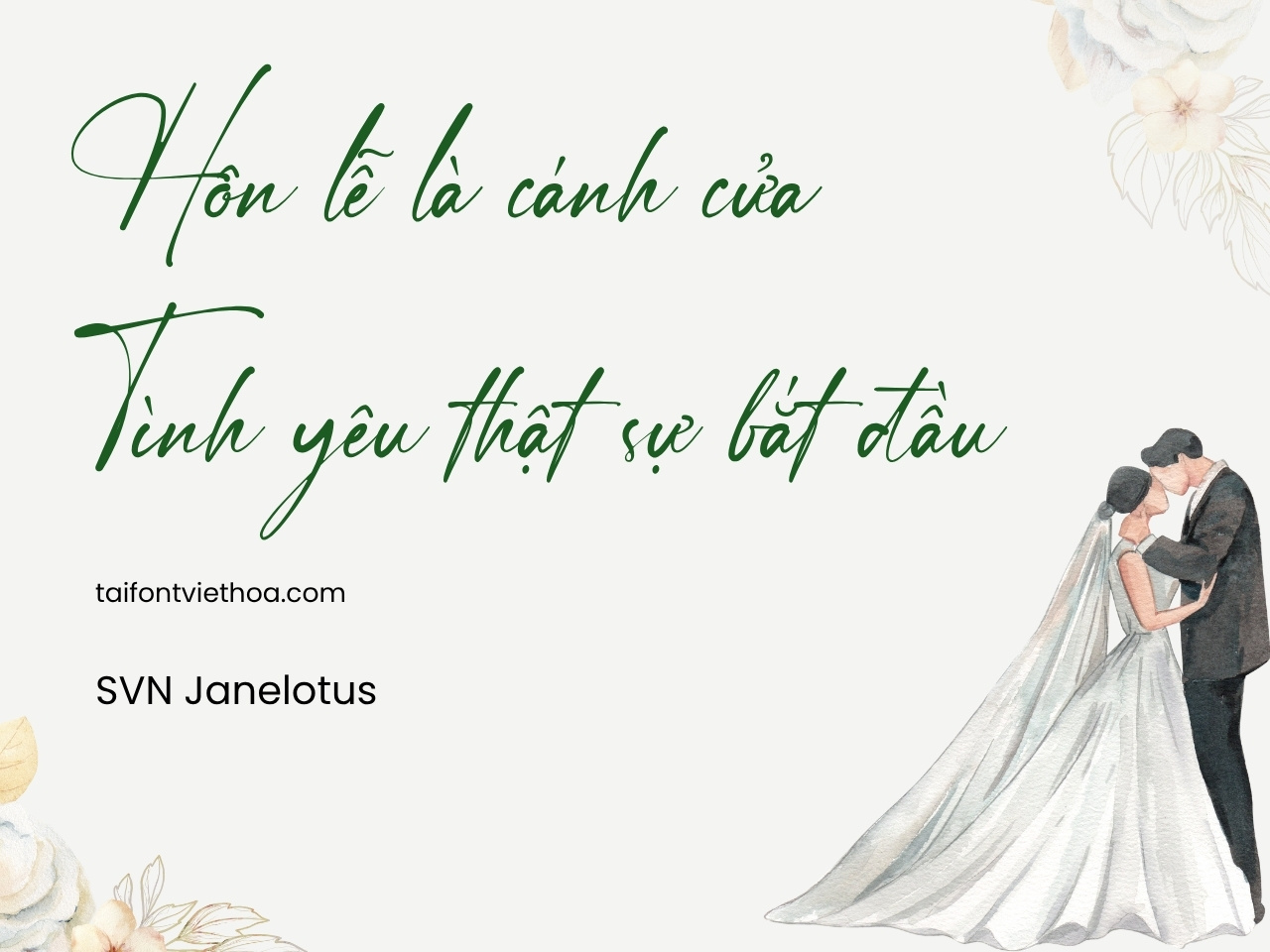
Font việt hóa SVN Janelotus
Giới thiệu về font SVN Janelotus – Kiểu chữ script viết tay mềm mại, tinh tế và duyên dáng
SVN Janelotus là phiên bản Việt hóa của font Janelotus – một kiểu chữ script mang phong cách viết tay uyển chuyển, nhẹ nhàng và đầy cảm xúc. Font được thiết kế để truyền tải sự thanh lịch, bay bổng và nữ tính, rất phù hợp cho các dự án thiệp cưới, lời chúc, thiết kế mỹ thuật và các sản phẩm sáng tạo cá nhân.
Phiên bản Việt hóa của SVN Janelotus đã được Taifontviethoa.comchăm chút kỹ lưỡng, hỗ trợ đầy đủ dấu tiếng Việt cùng hơn 60 ngôn ngữ khác. Font giữ nguyên nét mềm mại, uyển chuyển của bản gốc, giúp các nhà thiết kế dễ dàng áp dụng trong nhiều dự án sáng tạo với phong cách nữ tính và duyên dáng.
Thiết kế viết tay uyển chuyển – Lý tưởng cho thiệp cưới và thương hiệu mỹ phẩm
SVN Janelotus sở hữu các nét chữ mềm mại, mảnh mai, liền mạch với độ nghiêng nhẹ nhàng và các ligature tinh tế tạo nên sự hài hòa và bay bổng trong tổng thể thiết kế. Font mang lại cảm giác duyên dáng, sang trọng và rất phù hợp cho tiêu đề, logo, bao bì hoặc các phần thiết kế cần điểm nhấn mềm mại và nữ tính.
Ứng dụng lý tưởng: thiệp cưới, thiệp mời, logo thương hiệu mỹ phẩm, bao bì sản phẩm cao cấp, bìa sách nghệ thuật, poster sự kiện và các dự án sáng tạo cần sự mềm mại, duyên dáng. Ngành nghề phù hợp: cưới hỏi, mỹ phẩm, thời trang, nghệ thuật, truyền thông sáng tạo và các thương hiệu định vị theo phong cách nhẹ nhàng, thanh lịch.